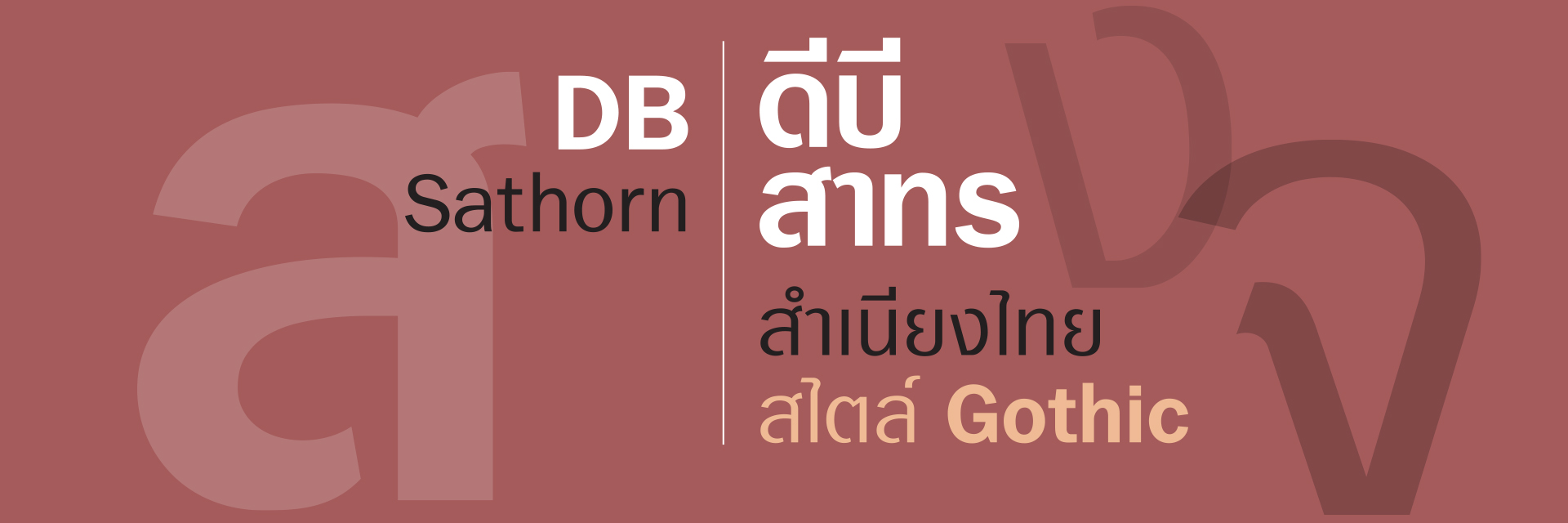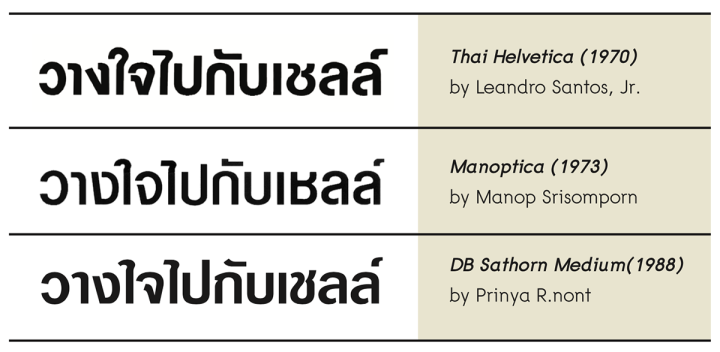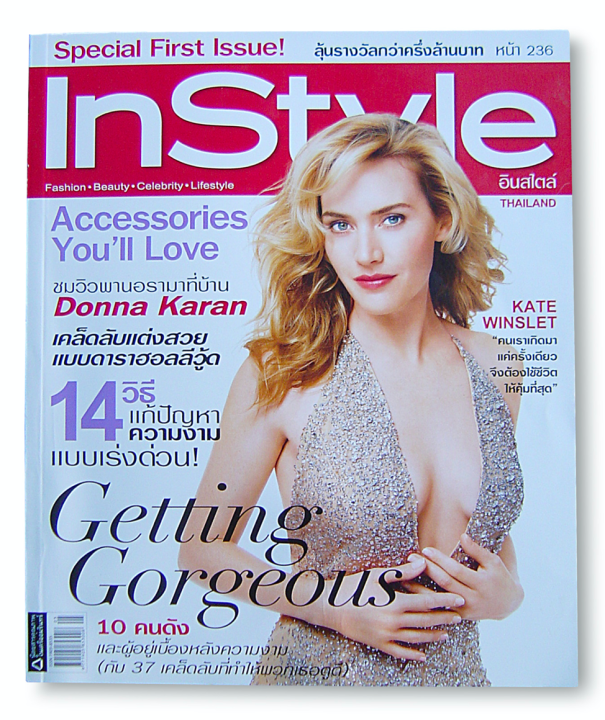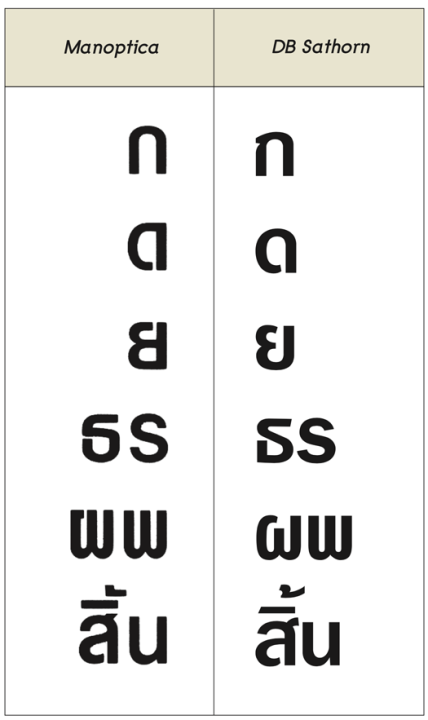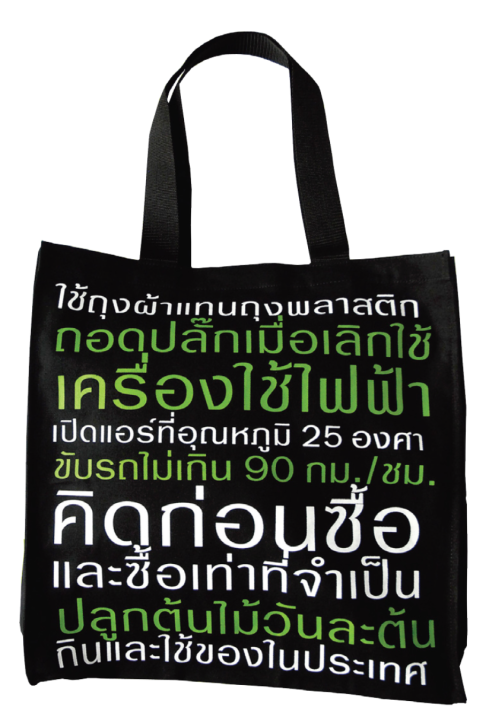
DB Sathorn คือความพยายามของผมที่จะสร้างฟอนต์ตัวพาดหัวไทย ที่สามารถทดแทนตัวอักษรลอกตระกูล Manoptica (มานพติก้า) ซึ่งครองเมืองในยุคที่คอมพิวเตอร์ยังไม่เป็นที่ใช้แพร่หลาย.
มันเป็นการยากมากสำหรับผม ที่จะออกแบบชุดอักษรไทยที่เลียนแบบ Helvetica ให้ได้ดีไปกว่า Manoptica ของอาจารย์มานพ ศรีสมพร (เนื่องจากเพิ่งมีประสบการณ์ทำฟอนต์พาดหัวมาแค่ 2 ตัว คือ DB PatPong และ DB Erawan) ฉะนั้นวิธีการที่ดีกว่าคือ หนี Manoptica ให้ได้!
การหลีกหนีจาก "ความเป็น Helvetica" ของ Manoptica ก็ยังนับเป็นปัญหาที่ยากอยู่ดี. เพราะถ้าหนีจนดูแตกต่างมากไปฟอนต์ที่ได้อาจห่างไกลจนคนเกิดความไม่คุ้นชินและพาลไม่เป็นที่นิยม. ผมพบคำตอบโดยบังเอิญด้วยความโชคดี ที่ก่อนออกแบบ DB Sathorn ไม่นาน คุณประชา สุวีรานนท์ เคยแวะมาที่บริษัทของผม ได้ตั้งข้อสังเกตไว้ขณะที่ไปศึกษาต่อที่ New York ว่า โฆษณาสิ่งพิมพ์ของอเมริกันนิยมใช้ตัว Franklin Gothic พาดหัวมากกว่า Helvetica. ข้อสังเกตของคุณประชานี้เอง ทำให้ผมตั้งคำถามว่า "ทำไมถึงเป็นเช่นนั้น?" จนนำไปสู่คำตอบในที่สุดว่าแนวคิดในการออกแบบฟอนต์ใหม่ควรเป็นอย่างไร.
ผมลองหาตัวอบ่าง Franklin Gothic มาเปรียบเทียบกับ Halvetica ดูตัวต่อตัว พิจารณาดูจะเห็นความแตกต่างสำคัญอยู่ข้อหนึ่งคือ Franklin Gothic ยังคงหลงเหลือเส้นหนักเบาของตัวพิมพ์ยุค classic ที่มี serif เอาไว้. ต้องยอมรับว่า stroke และ serif ของตัวพิมพ์ที่สืบทอดกันมานาน (ตั้งแต่ Jenson ที่ออกแบบในปี ค.ศ. 1470 มาจนถึง Times ตัว text ในหนังสือพิมพ์ Times ที่ฝรั่งคุ้นเคย) นั้น เป็นทั้งศิลปกรรมและ "เครื่องมือ" ในการแยกแยะลักษณะตัวพิมพ์แต่ละตัวให้ดูแตกต่างกัน ซึ่งทำให้อ่านได้ง่ายด้วย. ยิ่งถ้าสังเกตตัวอักษร g ให้ดี จะพบว่า g ของ Franklin Gothic มีความคล้ายคลึงของ Jenson ในขณะที่ g ของ Helvetica แตกต่างออกไป. ถึงตรงนี้, ด้วยสามัญสำนึกง่ายๆ ผมจึงเดาได้ (โดยไม่ทันต้องค้นคว้า) ว่า Franklin Gothic น่าจะเกิดก่อน Helvetica และตั้งสมมุติฐาน (ฟังดูน่าเชื่อถือกว่าคำว่าเดา) ได้ว่า เหตุที่โฆษณาอเมริกันช่วงนั้น ใช้ Franklin Gothic มากกว่า Helvetica ก็เพราะมันเป็นตัวพิมพ์ sans serif (sans แปลว่า ไม่, sans serif แปลว่า ไม่มี serif) ที่ดูใกล้เคียง serif มาตรฐาน ซึ่งฝรั่งคุ้นชินในชีวิตประจำวัน (ตั้งแต่ตัว text ในตำราจนถึงหนังสือพิมพ์รายวัน) จึงทำให้ Franklin Gothic สื่อสารได้ "จัง" กว่า. ขณะที่ Helvetica ซึ่งเกิดทีหลังยังเป็นเพียงตัวแทนของรูปลักษณ์ที่สะท้อนความเรียบง่ายของยุคสมัย (นั้น) มากกว่าที่จะให้ "สุ้มเสียง" ที่จริงจังตรงไปตรงมา อย่างที่ภาษาโฆษณา (ยุคนั้น) ต้องการ.
ผลจากการเปรียบเทียบข้างต้นทำให้ผมคลำเป้าหมายเจอ. แค่เพียงออกแบบชุดตัวอักษรไทยที่อยู่ระหว่าง Manoptica กับลายมือเขียนหรือตัวเนื้อไทยที่คนไทยคุ้นเคย เราก็จะได้ตัวพาดหัวสายพันธ์ุใหม่ที่แตกต่างออกไป (เหมือนกับที่ Franklin Gothic แตกต่างกับ Helvetica) กล่าวคือจะไม่เกลี้ยงเกลาเท่า Manoptica แต่สื่อสารได้ชัดเจนและจริงจังกว่า.
บรรดาตัวพาดหัวภาษาไทยซึ่งเข้าข่าย "เป้าหมาย" ที่ผมวางไว้นั้น, เท่าที่เคยผ่านตาของผมมีเพียงตัวอักษรที่ใช้เป็น Slogan ของ Shell ที่ว่า "วางใจไปกับเชลล์" ผมจดจำตัว ง จ และ ช ได้อย่างติดตา เป็นเพราะมันแตกต่างจากของ อ.มานพ อย่างเห็นได้ชัด (ดูภาพประกอบด้านบน) เป็นผลงานของ Leandro Santos, Jr. หรือคุณบอย นักออกแบบเรขศิลป์ชาวฟิลิปปินส์ ในปี พ.ศ. 2513 ซึ่งเป็นปีแรกที่เข้ามาอยู่เมืองไทยทำงานกับบริษัทโฆษณา Ogilvy & Mather. ด้วยความที่ไม่รู้จักภาษาไทยของคุณบอยจึงพยายามออกแบบให้คล้ายตัวไทยมาตรฐานเข้าไว้ (เพื่อความมั่นใจว่าคนไทยจะอ่านรู้เรื่อง!) ผมประทับใจงานของคุณบอยมาก เพราะว่ามันเป็นส่วนผสมที่ลงตัวระหว่างความเรียบง่ายทันสมัยอย่าง Helvetica กับความอ่านง่ายแบบไทยๆ ไว้ด้วยกัน.
แม้ในขณะกำลังลงมือออกแบบผมจะไม่มี "วางใจไปกับเชลล์" ให้ดู (เพราะค้นหาไม่เจอ) ก็ตาม แต่ตัวอักษร ง จ และ ช ยังถูกเก็บไว้อย่างดีในสมอง. มันเปรียบเสมือนตอม่อที่คุณบอยทำไว้ให้ผมสร้างต่อเป็นสะพานเชื่อมโยงระหว่างตัวอักษรไทยยุคใหม่ที่ยึดโยงอยู่กับตัวโรมันของโลกตะวันตก กับตัวอักษรไทยมาตรฐานซึ่งเป็นรากเหง้าของเราเอง. ผมเริ่มงานออกแบบชิ้นนี้ด้วยการเดินไปซื้อแผ่นอักษรลอก Franklin Gothic Medium จากห้างสยามวาลา ที่อยู่ใกล้ๆ บริษัทของผม เอามาลองตัดต่อผสมเป็นตัวอักษรไทยได้ไม่กี่ตัว! เช่น ตัดตัว a ให้เป็นตัว ล แล้วตัด ear ของตัว g มาต่อกับ ล ให้เป็น ส, ตัด crossbar ของตัว e ออกได้เป็นตัว อ. ตัว ท, น, ร, ว ได้จากตัว n, u, s และ c ตามลำดับไม่ต้องออกแรง. ตัวที่เหลือเป็นส่วนใหญ่ ผมต้องร่างด้วยดินสอแทบทั้งหมดเพื่อให้มัน "ดูเป็นไทย" มากขึ้น.
DB Sathorn บนปกนิตยสาร "InStyle (Thailand)" ฉบับปฐมฤกษ์
เริ่มจากตัว จ และ ช ที่ได้เค้าโครงมาจากของคุณบอย (ซึ่งเป็น DNA ที่ส่งผ่านมาถึง DB Sathorn) ยังคงถูกรักษาลักษณะเด่นไว้ คือ ตัว จ มีเส้นตรงสอบเข้าทำมุมที่ฐาน และตัว ช มีเส้นขมวดหัวชัดเจน. สิ่งที่เปลี่ยนไปเล็กน้อย คือ ปลายส่วนหัวของตัวอักษรถูกตัดแนวทะแยง ไม่เหมือนชุดตัวอักษรของคุณบอย ที่ปลายหัวและหางตัดตามแนวดิ่งและแนวนอนอย่าง ending ของ Helvetica ทุกตัว (ยกเว้นปลายหางตัว ง). หางตัว ช ถูกต่อเติมให้สูงขึ้นเลยเส้นบนเล็กน้อยเพื่อความชัดเจน. ส่วนตัว ง นั้น เพื่อไม่ให้ดูแปลกแยกจนเกินไปจาก Manoptica ที่นักออกแบบส่วนใหญ่เวลานั้น (รวมทั้งผมด้วย) คุ้นเคย ผมจึงทำแค่เพียงลดระดับหางของมันให้ต่ำลง เพื่อให้อ่านได้ง่ายเหมือนตัว ง ของคุณบอย แต่ยังคงเส้นหลังโค้งของ อ.มานพ ไว้.
• ตัว ก เป็นการพบกันครึ่งทางระหว่างใหม่เก่า. เส้นรอบ (outline) ด้านในเกลี้ยงเกลา ส่วนด้านนอกมีรอยหยักปากให้เด่นชัด (ทำให้ตัว ถ ไม่ไปสับสนกับ ด).
• ทั้ง ด และ ย ของ Manoptica ที่มีเส้นหลังทำมุมฉากกับเส้นบนและเส้นฐานตามลำดับนั้น ถูกปรับใหม่ให้โค้งมนแบบลายมือเขียนเพื่อเพิ่ม "ที่ว่าง" ด้านหลังให้กับมัน จะได้ไม่ดูทึบเมื่อถูกพิมพ์ต่อเนื่องด้วยสระ เ, แ หรือ ตัว ท, ม, ห ของชุดนี้ (อย่าลืมว่าไม่มีหัว) ซึ่งล้วนมีเส้นหนาตรงทึบโดยไม่มีส่วนโค้งใดๆ ช่วย.
• ตัว ธ เกิดจากการปรับเส้นบนและเส้นฐานของตัว s ให้เหยียดตรงในแนวนอน เพื่อให้ดูต่างจาก ร ได้อย่างสิ้นเชิงไม่สับสน (ใน DB Sathorn ที่เป็น OpenType Font ตัว ธ คงเหลือแต่เส้นบนตรง ส่วนเส้นฐานปรับโค้งเพื่อให้ดูราบรื่นขึ้น).
• ตัว ผ, ฝ มีหัวโค้งงุ้มเข้าลําตัวเห็นๆ (เป็นDNA ที่ถ่ายทอดมาจาก DB PatPong และ DB Erawan ซึ่งออกแบบมาก่อนหน้า) อีกทั้ง ระดับเส้นกลางจะอยู่ต่ำกว่าแนวเส้นบนเพื่อให้แยกแยะออกจาก พ, ฟ (ซึ่งมีเส้นกลางเสมอแนวเส้นบน) ได้อย่างชัดเจน.
• หางตัว ส ที่ได้จากการตัดต่อ ear ตัว g ของ Franklin Gothic เข้ากับตัว a ของมันนั้น ลักษณะที่เอนหลบซ้ายออกจากเส้นชาน หลังช่วยให้สามารถหลบพ้นจากสระบน (ทําให้เห็นหางเสือได้ชัด แม้ใช้ในขนาดเล็กๆ ก็ไม่สับสนเป็นลิง!).
DB Sathorn X (2005)
การได้เรียนรู้จากผลงานระดับอาจารย์ 2 ท่าน ประกอบกับรายละเอียดมากมายที่ปรุงแต่งเข้าไป ทําให้ DB Sathorn Usรลุเป้าหมายที่วางไว้ แม้ว่า billboard ของใครจะอยู่ใกลสูงลิบ, แม้ว่าทีวีบ้านใครคลื่นไม่ชัดแจ๋ว, แม้ว่าสิ่งพิมพ์ฉบับใหนจะปล่อยหมึกหนักไปบ้าง หรือใช้ตัวพิมพ์ขนาดเล็กไปบ้าง ฯลฯ, DB Sathorn ก็ยังคงทําหน้าที่ที่ดีของมัน อย่างไม่รู้เหน็ดเหนื่อย... นั่นคือถ่ายทอดสาระ ด้วยสุ่มเสียงที่ชัดเจนเสมอ.
DB Sathorn บนถุงผ้า โดยนิตยสาร "สารคดี"
วรรณยุกต์  ้ ซึ่งมีที่ใช้มากในภาษาไทย ผมจําเป็นต้องตัดใจ ทิ้งหางโค้งขึ้น เพื่อให้แยกแยะออกจากตัว   ั (ซึ่งหางเหยียดตรงใน แนวนอน) ได้ง่าย. ทั้งปลายซ้ายของสระ   ิ และปลายหางของ   ั ถูกตัดเฉียงเพื่อให้ดูง่ายว่าตรงไหนหัวไหนหาง โดยเฉพาะปลายซ้าย ของ อิ อี อึ อื ทั้งชุด เลี่ยงที่จะตัดแนวดิ่งมาเป็นทะแยงเฉียงก็เพื่อเป็น การชดเชยความกว้างที่ไม่เท่ากันของตัวพยัญชนะไทย (อักษรลอก Manoptica ของ อ.มานพ ก้าวหน้าใส่ใจในรายละเอียด โดยมีชุด สระ   ิีึื ให้เลือกใช้ถึง 3 ขนาดตามความกว้างของพยัญชนะ แต่ Technology ของฟอนต์ในยุคแรกเริ่มยังตามไม่ทัน เพิ่งมาทําได้ ในยุคนี้ที่เข้ารหัสอักษรเป็น Unicode ซึ่งเก็บรูปอักษรได้มากมาย ความกว้างของสระจึงไม่ถูกจํากัดอีกต่อไป).
ด้วยแผ่นอักษรลอก, เครื่องมือขุด, คัตเตอร์, ดินสอ, และ กระดาษ ถูกส่งผ่านเป็นต้นแบบใช้ในโปรแกรมสร้างฟอนต์ ที่ถูก ให้ชื่อโดยคุณสุรพล เวสารัชเวศย์ว่า DB Sathorn. ถ้าให้ผมตั้งเอง ณ ตอนนี้ ผมเรียกมันว่า DB Franklin Gothai เพื่อจะได้รู้กันชัดๆ ไปเลยว่า เป็นตัวพาดหัวไทยที่เลียนความเป็น Franklin Gothic, ไม่ใช่แค่เพียงผิวเผิน, หากลงลึกถึงรากวัฒนธรรมของไทยเราเอง